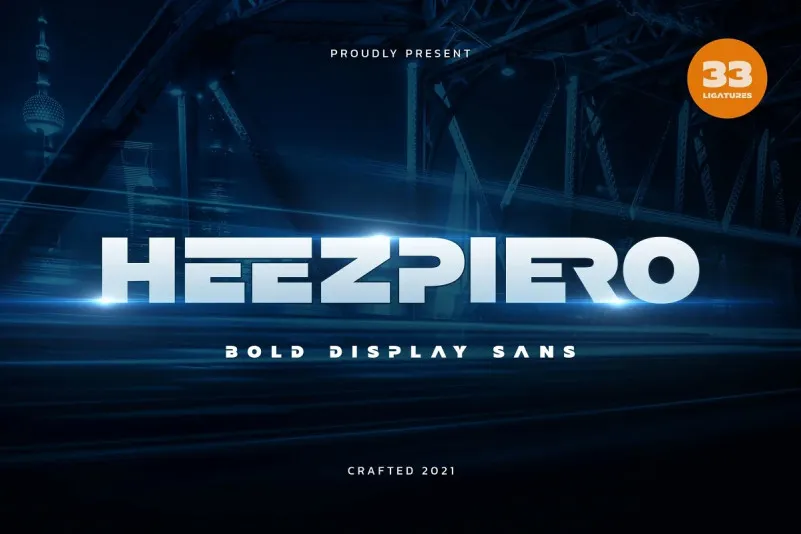
A “Heezpiero Font” é uma elegante tipografia sans-serif cuidadosamente projetada para criar trabalhos de tipografia atraentes e ativos. Suas linhas sólidas e fortes permitem que você crie obras visuais agressivas e vibrantes, idealmente para uso em logotipos, rótulos, embalagens ou camisetas de desenho animado. Foi inspirada nos logos icônicos de tecnologia e marcas conhecidas por suas características fortes, tornando-a uma opção perfeita para a criação de identidades visuais. Este tipo de fonte tem 33 ligaturas personalizadas, o que adiciona ainda mais diversidade às suas criações. A “Heezpiero Font” é um recurso valioso para designers gráficos em busca de uma tipografia poderosa e versátil.